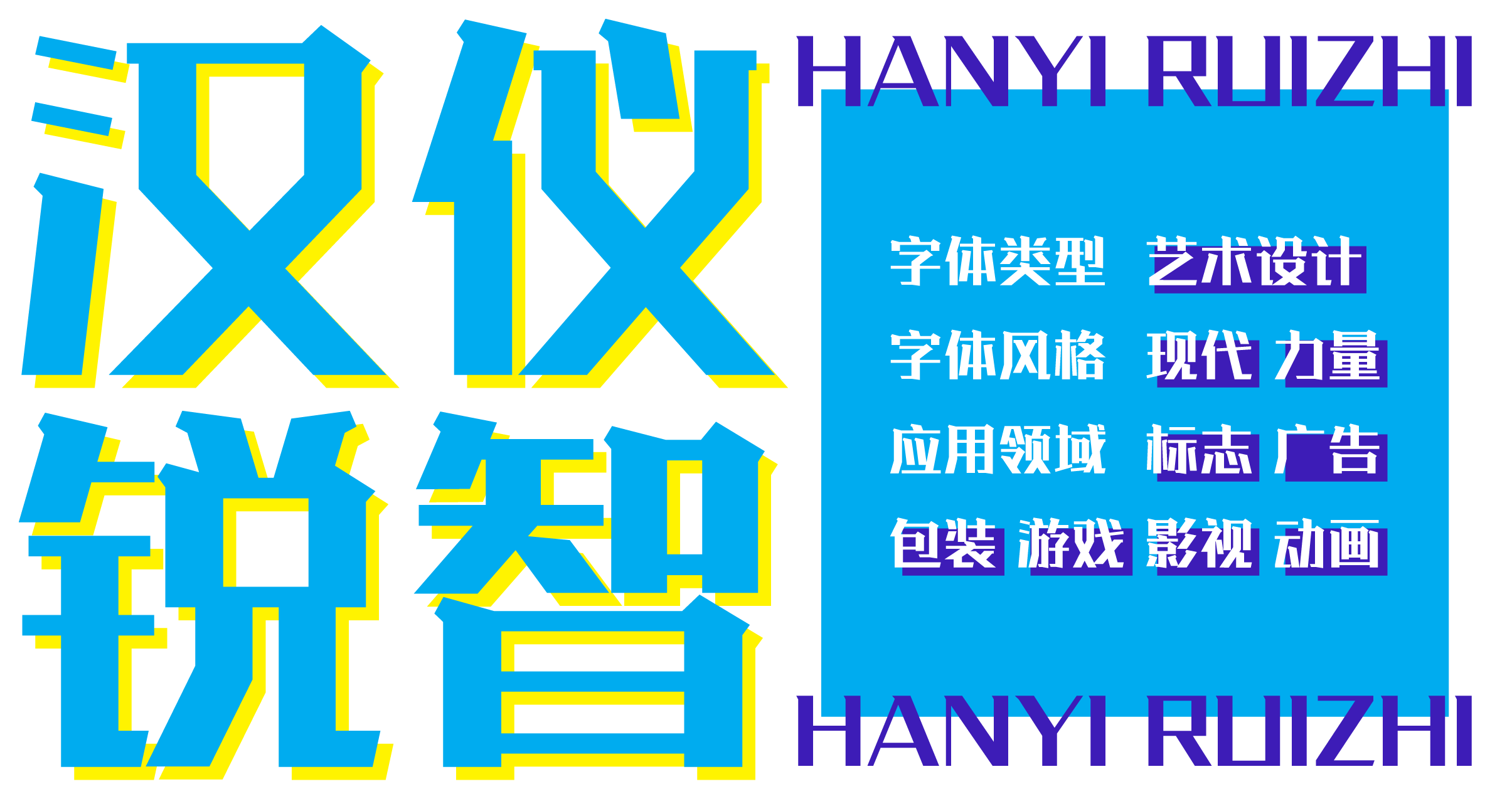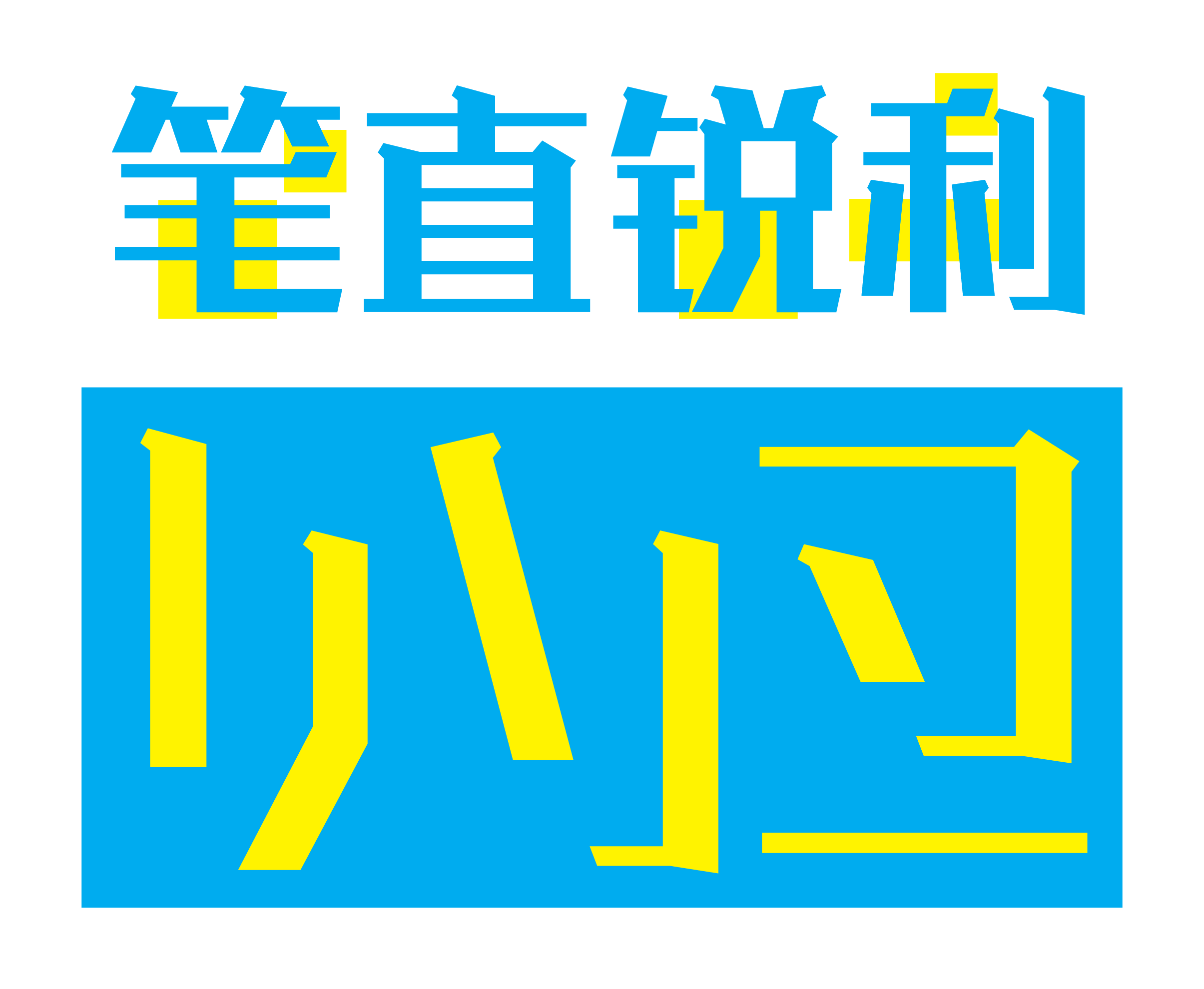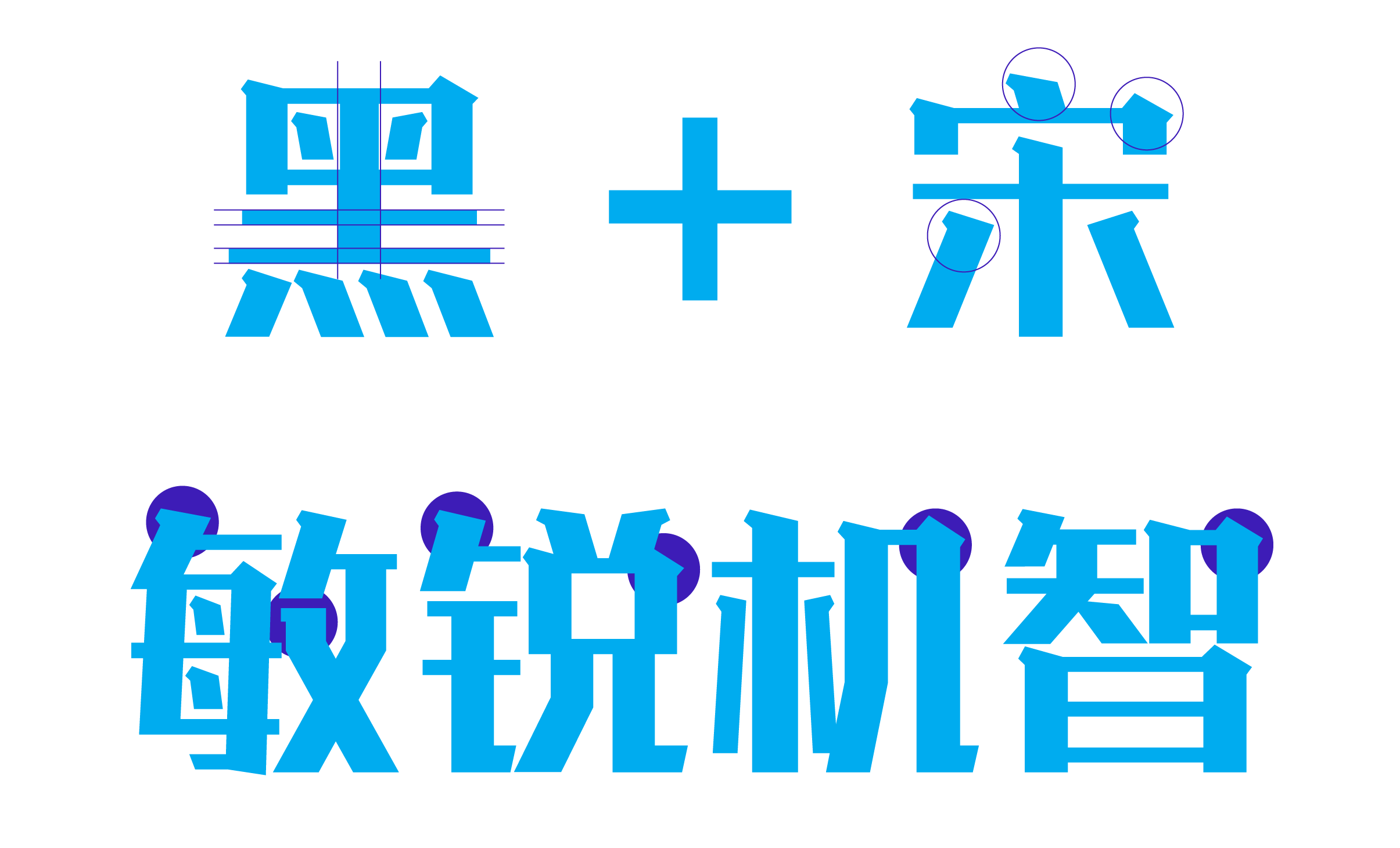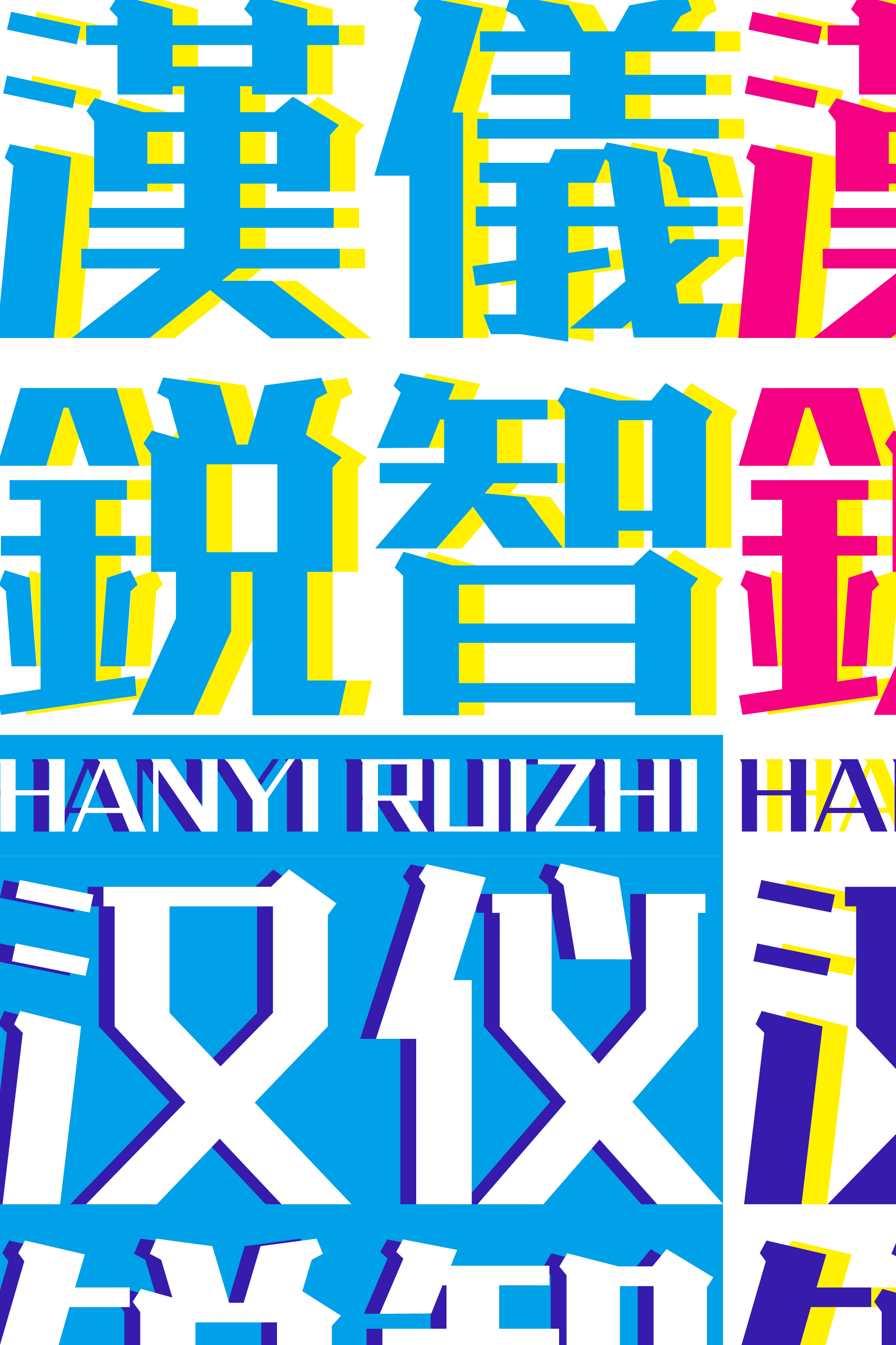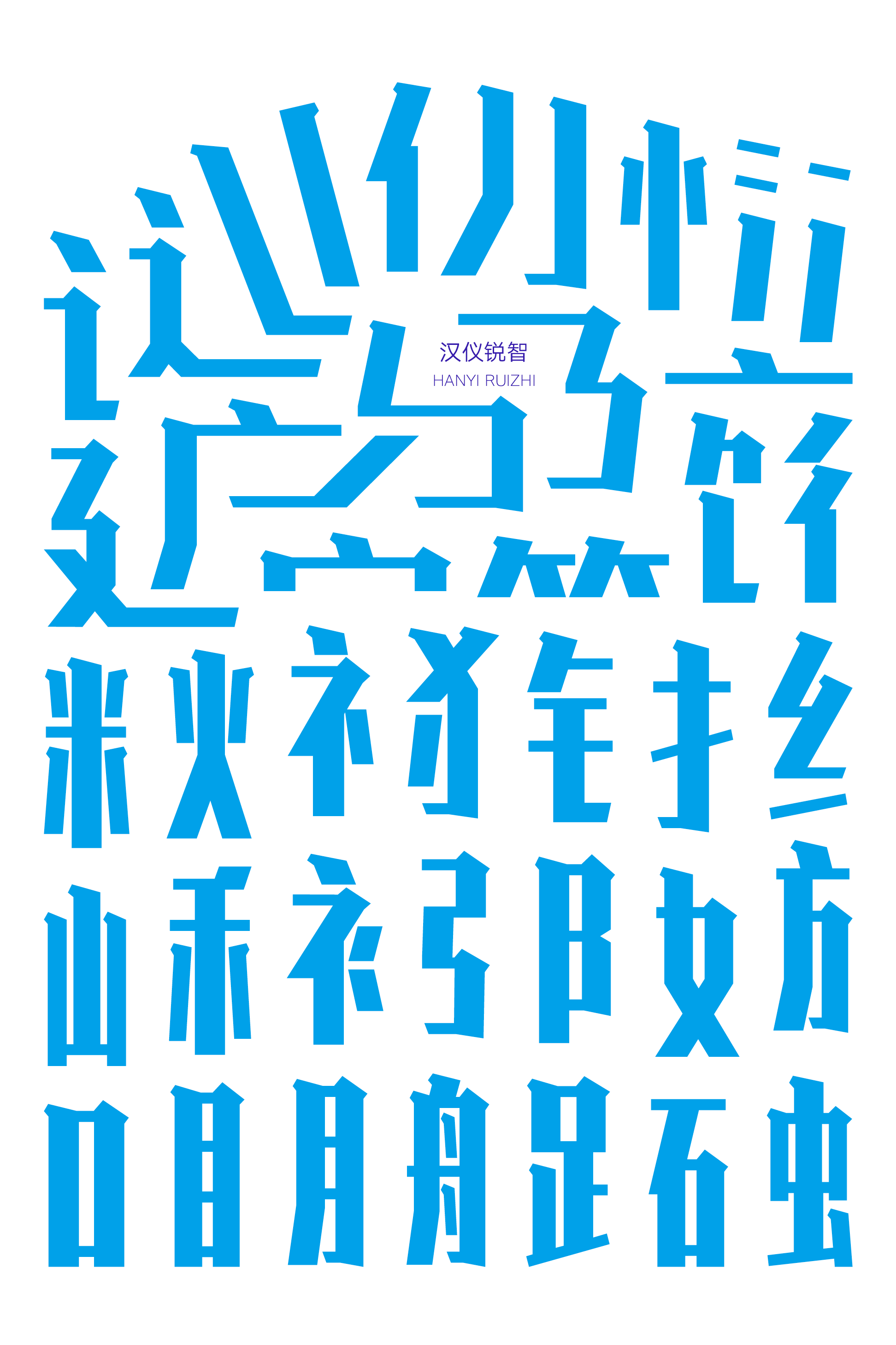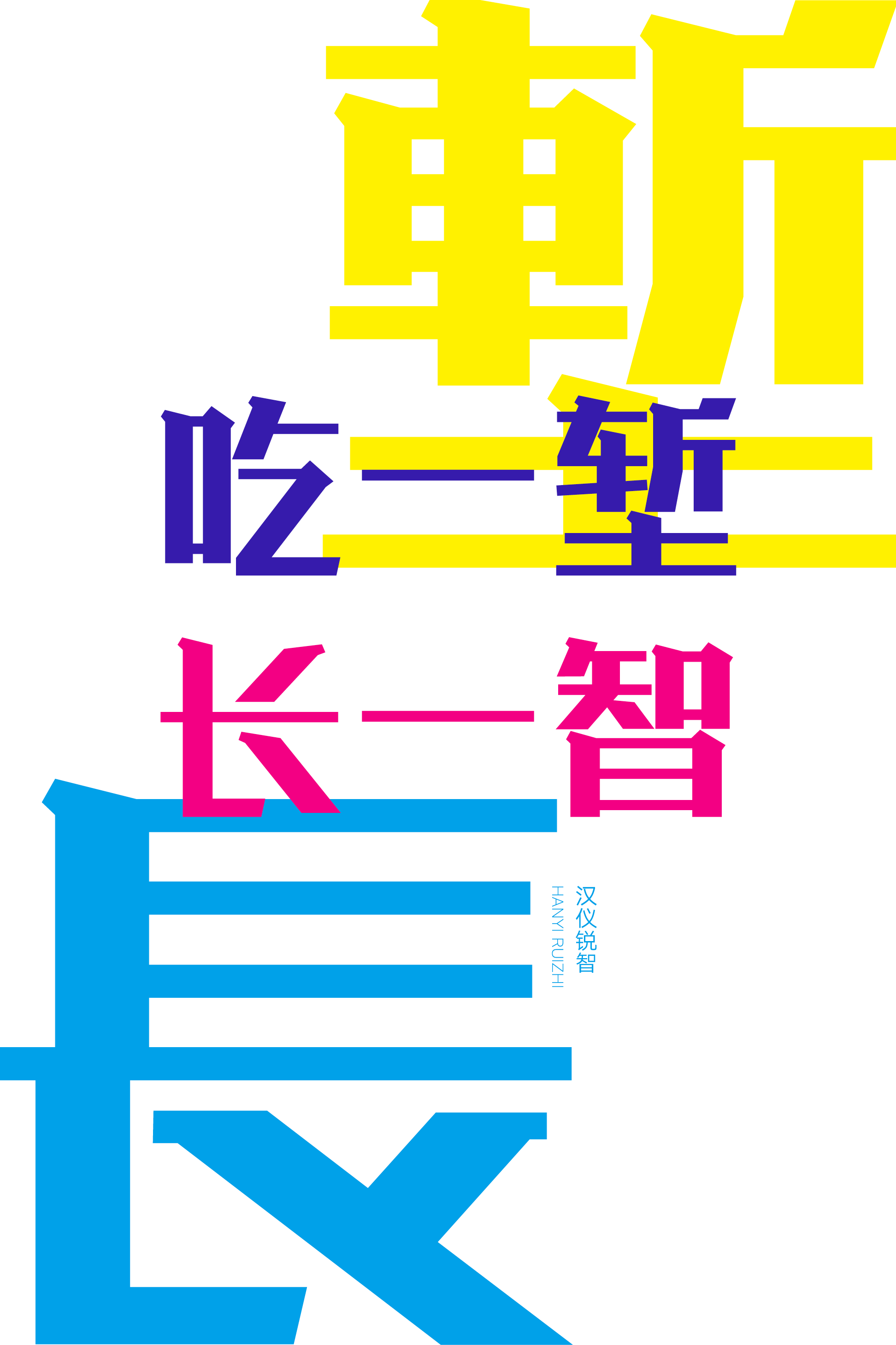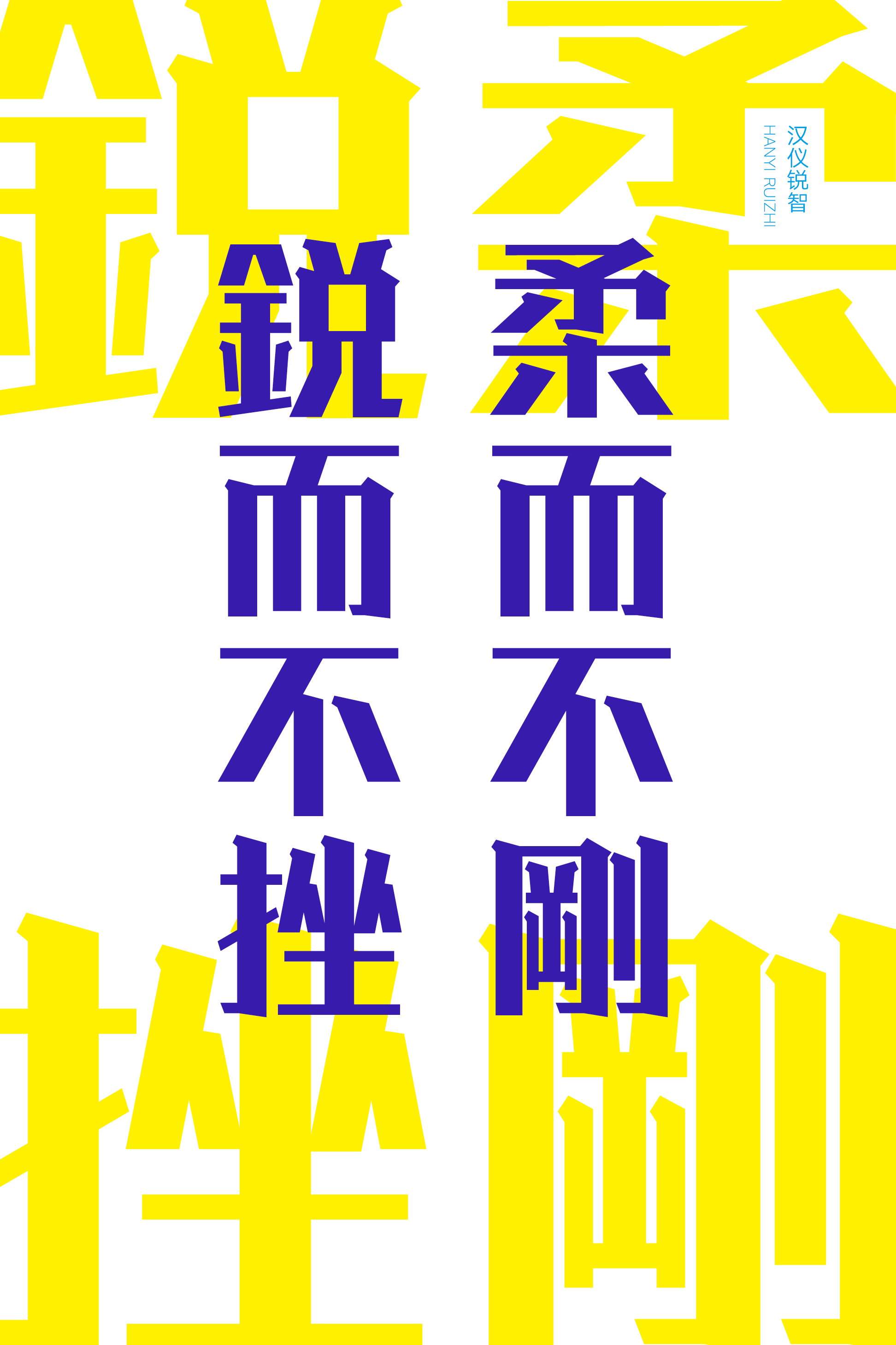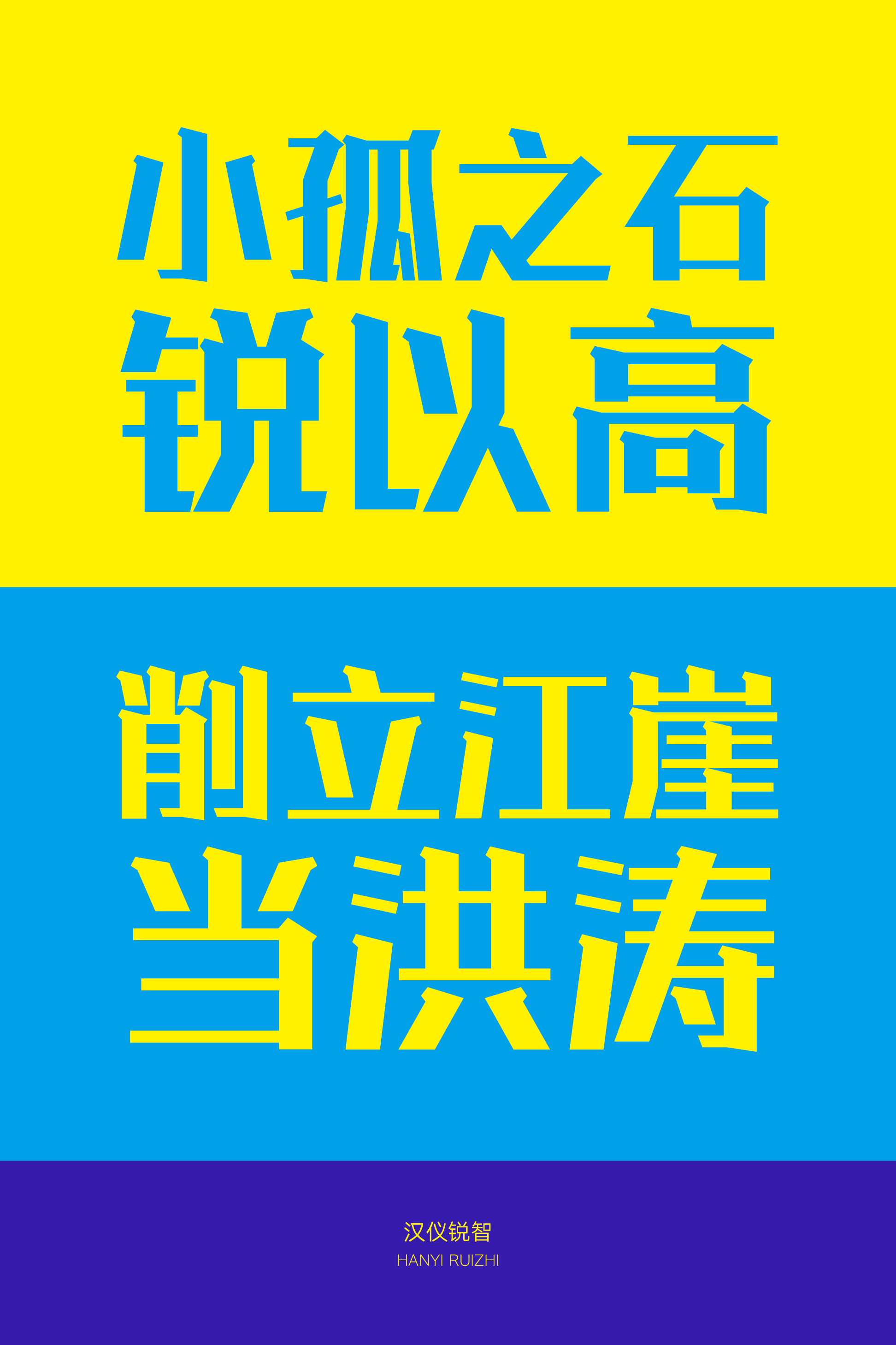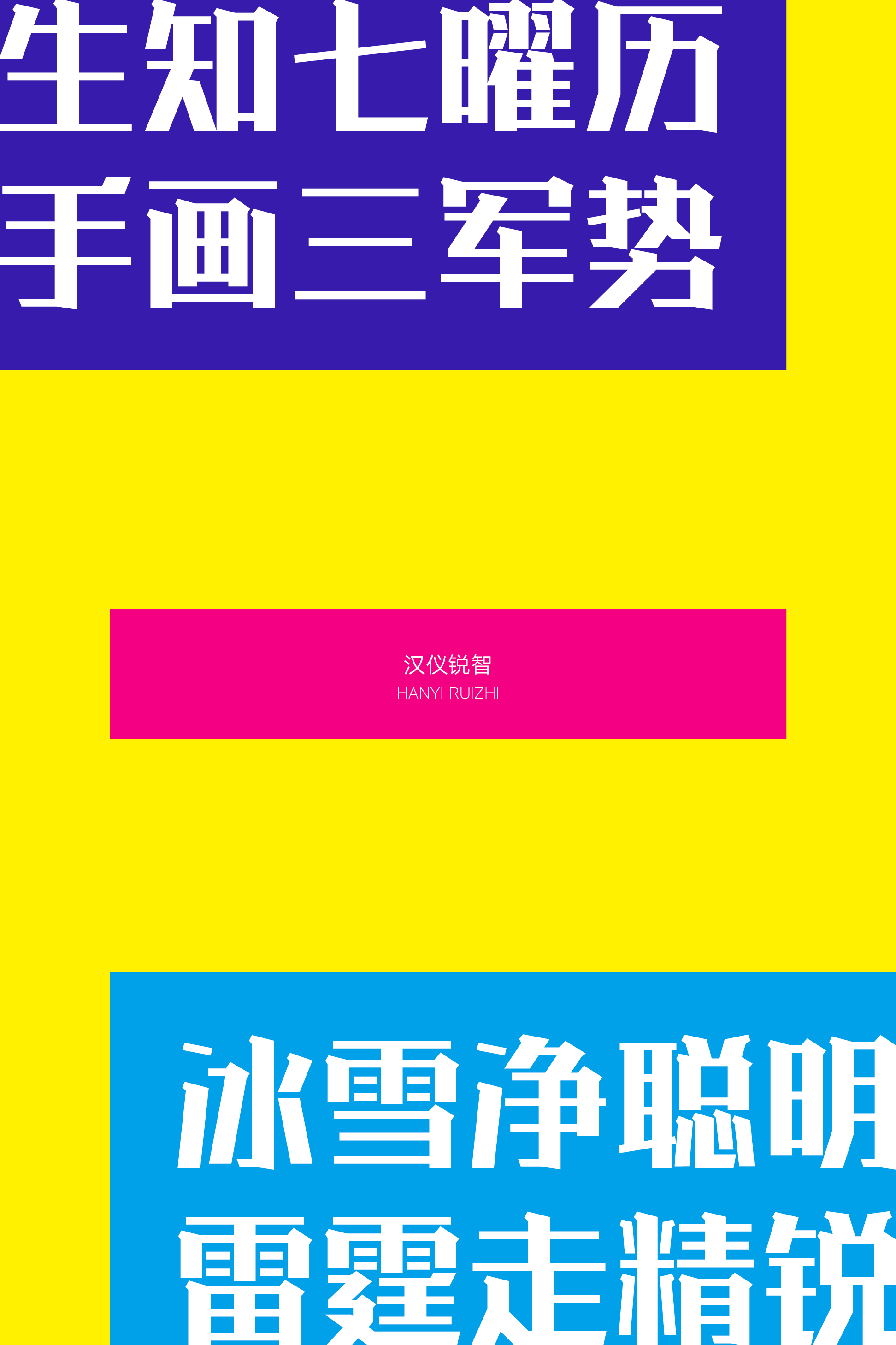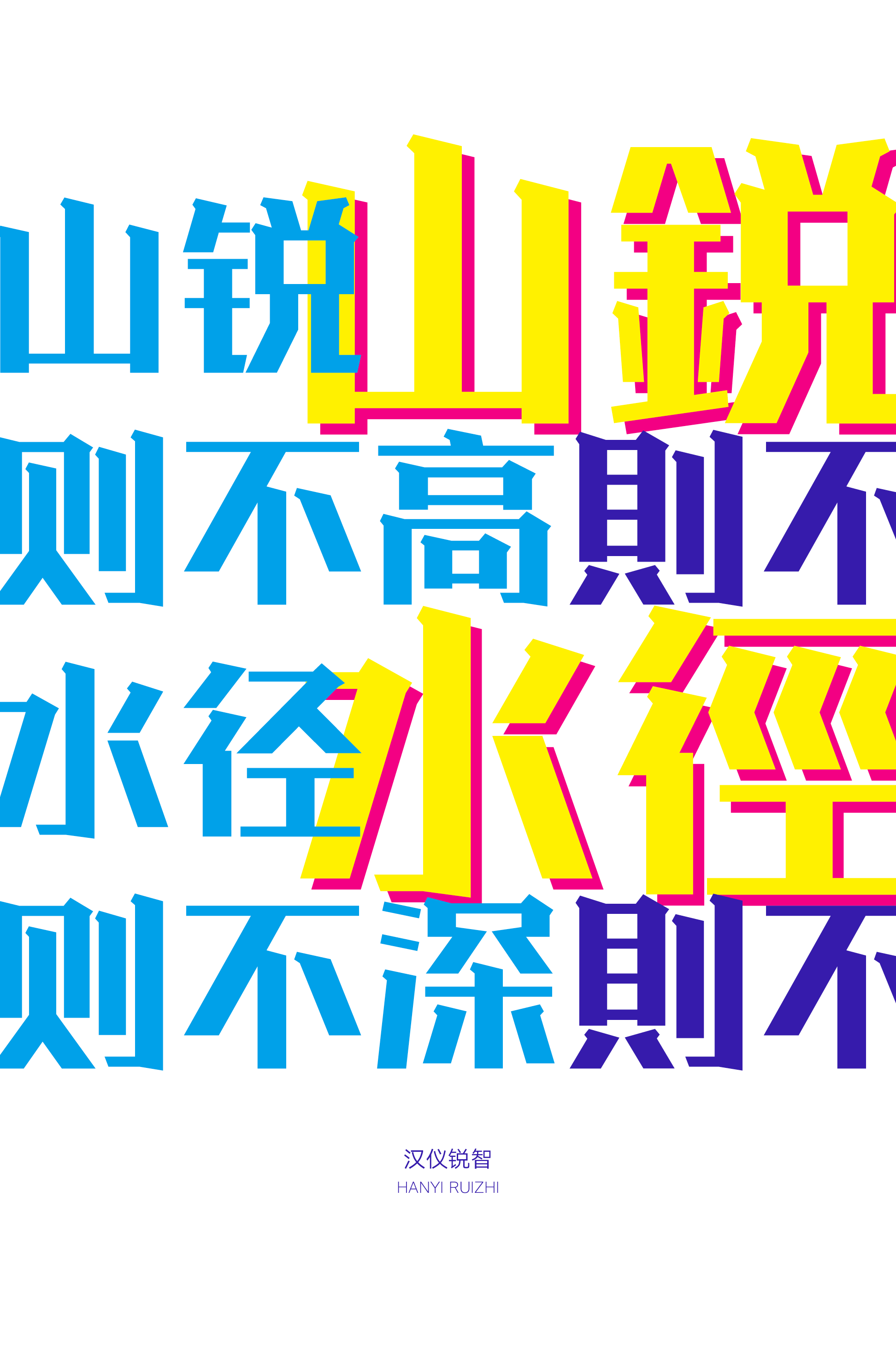
汉仪锐智
汉仪锐智是一款现代而有力量的标题字体。结构简洁清晰,线条笔直刚硬,以方折代弧线,对笔画线条进行了几何化的处理,加入简略处理的宋体衬角,使得整体现代简洁而拥有丰富的细节。这款标题字体敏锐又机智,适应各种各样的使用场景,无论品牌标识、广告包装、影视娱乐,势不可挡。
字形方直规整,结构简洁清晰。
线条笔直刚硬,进行了几何化处理。
加入宋体的衬角特征,并作简略处理。
西文部分线条同样笔直刚硬,加入锐利的三角衬线以匹配中文部分。